세계적으로 성공한 CEO들은 개성 넘치는 싸인을 가지고 있어요. 이들의 싸인은 단순한 서명이 아니라 브랜드 아이덴티티와 리더십을 상징하기도 해요. 🏆
예를 들어, 빌 게이츠(Bill Gates)의 싸인은 가독성이 뛰어나고, 일론 머스크(Elon Musk)의 싸인은 빠르고 다이나믹한 느낌을 주죠. 그렇다면, 이들의 싸인은 어떤 특징을 가지고 있을까요? 🔍
지금부터 유명 CEO들의 싸인을 하나씩 분석하면서, 성공한 사람들이 선호하는 싸인의 공통점을 찾아볼게요! 🚀
CEO 싸인의 의미 💼
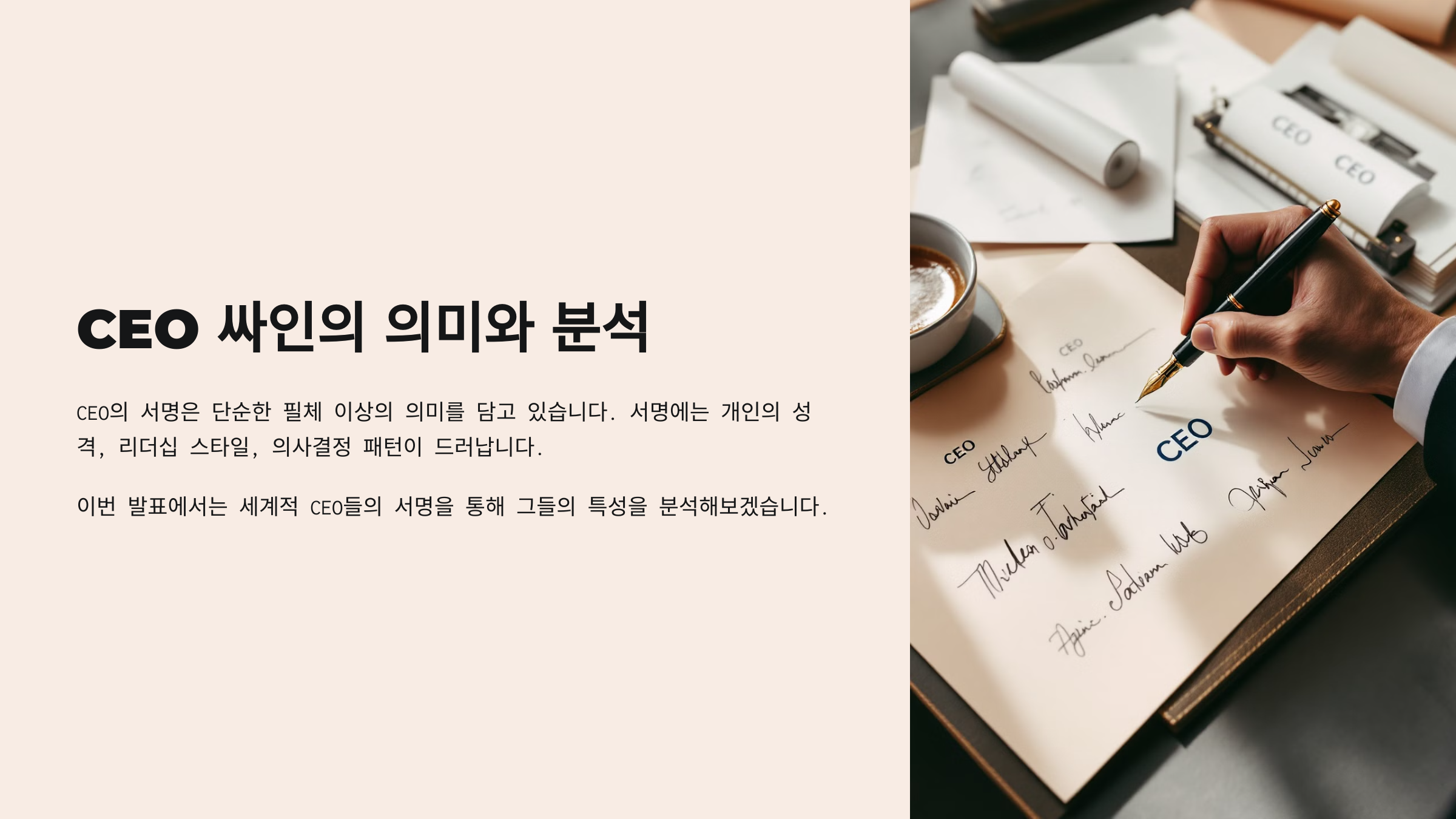
CEO들의 싸인은 단순한 서명이 아니라 그들의 리더십, 브랜드, 비전을 반영하는 요소예요. 싸인의 스타일만 봐도 그 사람의 성격과 경영 철학을 어느 정도 유추할 수 있어요. 🖋️
예를 들어, 빌 게이츠의 싸인은 정갈하고 깔끔한 반면, 일론 머스크의 싸인은 빠르고 역동적이죠. 이처럼 싸인은 단순한 이름의 기록이 아니라 CEO의 아이덴티티를 나타내는 상징이 될 수 있어요. 🔥
📌 CEO들의 싸인이 주는 의미 🔍
싸인 스타일 특징 대표 CEO 깔끔하고 정갈한 싸인 가독성이 뛰어나고 신뢰감을 줌 빌 게이츠 빠르고 다이나믹한 싸인 창의적이고 도전적인 이미지 일론 머스크 심플한 미니멀 스타일 최소한의 획으로 효율성을 강조 스티브 잡스 곡선적이고 부드러운 싸인 유연성과 협업을 중시하는 경영 스타일 제프 베이조스 이제 CEO들의 싸인이 어떤 의미를 가지는지 알았어요! 그럼 먼저, 빌 게이츠의 싸인을 분석해 볼까요? 🔍
빌 게이츠의 싸인 분석 🖋️
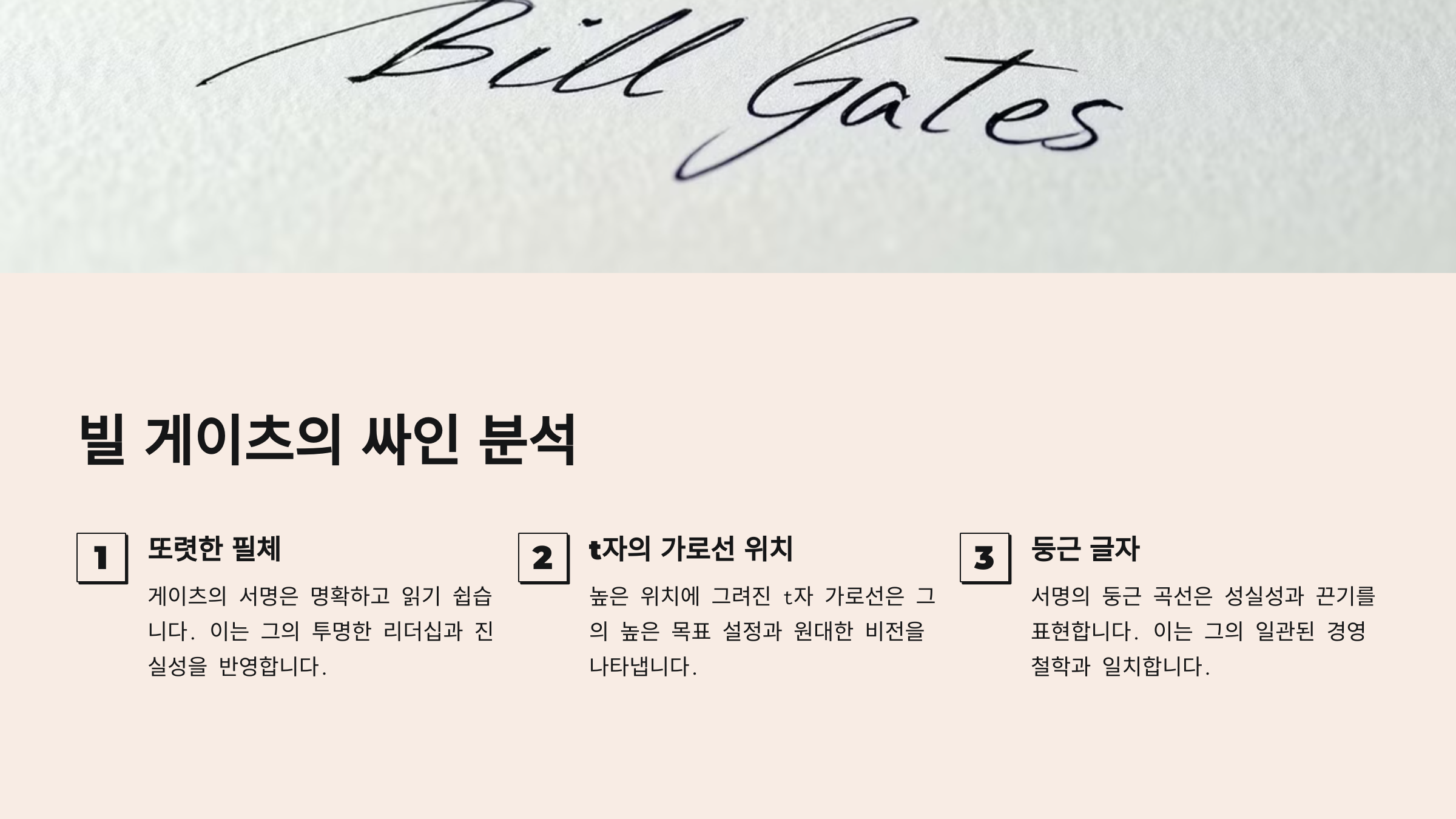
빌 게이츠(Bill Gates)는 마이크로소프트(Microsoft)의 공동 창립자로, 그의 싸인은 그의 성격과 경영 철학을 반영하고 있어요. 💡
그의 싸인은 깔끔하고 정갈한 글씨체로 되어 있으며, 가독성이 뛰어나고 신뢰감을 주는 것이 특징이에요. 이는 그가 논리적이고 체계적인 사고를 중시하는 리더라는 점을 보여줘요. 📜
📌 빌 게이츠 싸인의 주요 특징 ✅
특징 설명 가독성이 뛰어난 필기체 한 글자 한 글자가 명확하게 보이며 정돈됨 깔끔하고 균형 잡힌 구조 획이 정렬되어 있으며 일관성이 유지됨 부드럽지만 강한 마무리 끝부분이 확실하게 닫혀 있어 신뢰감을 줌 논리적인 성향 반영 체계적이고 실용적인 스타일 빌 게이츠의 싸인은 가독성 있는 스타일을 선호하는 사람들에게 좋은 참고 자료가 돼요. 그럼 이제 일론 머스크의 싸인은 어떻게 다를까요? 🚀
일론 머스크의 싸인 분석 🚀
일론 머스크(Elon Musk)는 스페이스X, 테슬라, 뉴럴링크 등의 CEO로, 그의 싸인은 그의 혁신적이고 도전적인 성향을 반영하고 있어요. 💡
그의 싸인은 빠르게 휘갈겨 쓴 듯한 다이나믹한 필체로, 강한 추진력과 변화를 추구하는 그의 성격을 잘 보여줘요. 이는 즉흥적이지만 강한 결단력을 가진 리더의 스타일을 나타내죠. ⚡
📌 일론 머스크 싸인의 주요 특징 ✅
특징 설명 빠르고 역동적인 필기체 획이 길고 속도감이 느껴지는 스타일 약간의 불규칙성 즉흥적인 스타일로 변화와 혁신을 상징 강한 획과 강조된 마무리 마지막 획이 강조되어 강한 리더십을 표현 개성 넘치는 스타일 전형적인 형식을 따르지 않고 자유롭게 구성됨 일론 머스크의 싸인은 창의적이고 독창적인 스타일을 원하는 사람들에게 좋은 참고 자료가 돼요. 그럼 이제 스티브 잡스의 싸인은 어떻게 다를까요? 🍏
스티브 잡스의 싸인 분석 🍏
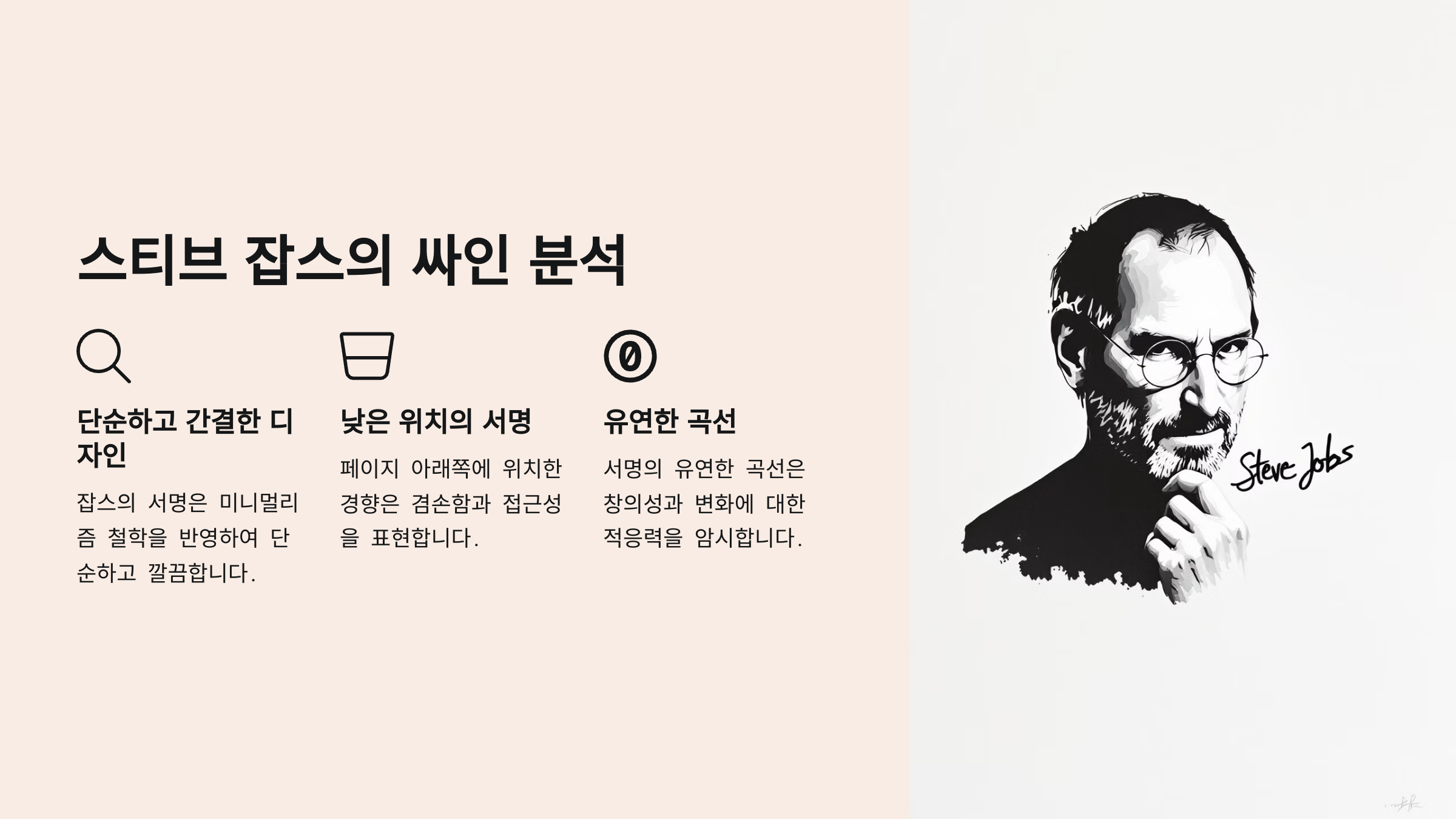
스티브 잡스(Steve Jobs)는 애플(Apple)의 공동 창립자이자 혁신적인 기업가로 유명해요. 그의 싸인은 그의 미니멀한 철학과 심플한 디자인 원칙을 반영하고 있죠. 🎨
잡스의 싸인은 단순하지만 강한 개성을 가진 필기체로 이루어져 있으며, 특히 획이 일정하고 명확한 글씨체가 특징이에요. 이는 그가 불필요한 것을 제거하고 본질만 남기는 사고방식을 가지고 있었다는 걸 보여줘요. ✍️
📌 스티브 잡스 싸인의 주요 특징 ✅
특징 설명 미니멀한 디자인 불필요한 장식 없이 깔끔하고 단순한 서체 일관된 글씨체 획이 고르게 유지되며 정리된 느낌 강한 개성과 명확한 구조 획이 과하지 않으면서도 강한 인상을 줌 균형 잡힌 형태 전체적으로 정돈된 느낌을 줌 스티브 잡스의 싸인은 심플하면서도 개성이 강한 싸인을 원하는 사람들에게 좋은 참고 자료가 돼요. 그럼 이제 제프 베이조스의 싸인은 어떻게 다를까요? 🚀
제프 베이조스의 싸인 분석 🚀
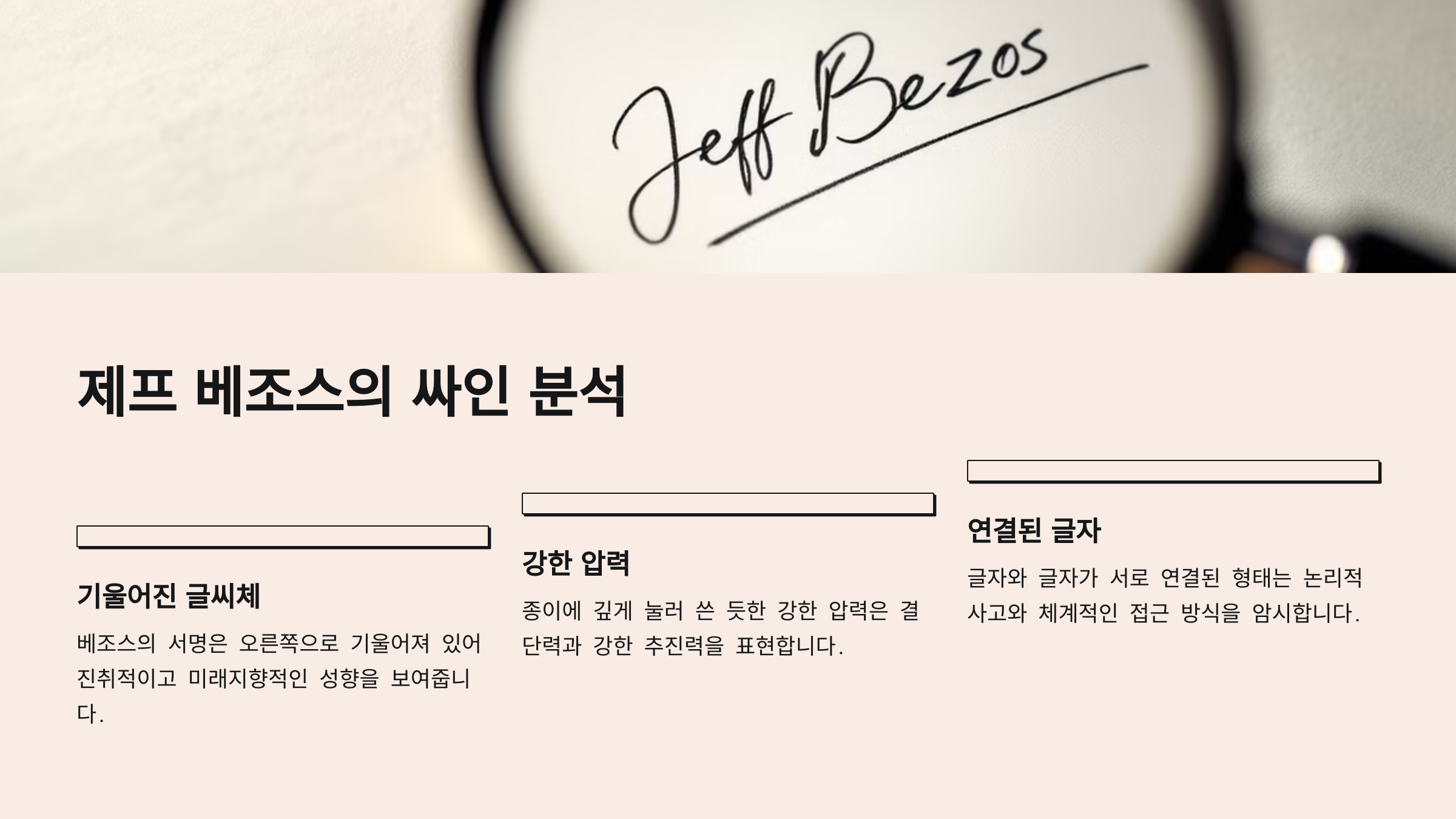
제프 베이조스(Jeff Bezos)는 아마존(Amazon)의 창립자이자 전 CEO로, 그의 싸인은 유연하면서도 힘 있는 필체를 보여줘요. 📦
베이조스의 싸인은 곡선이 많고 부드러운 필기체로 이루어져 있으며, 특히 글자 사이가 넓고 흐름이 자연스럽게 연결되는 것이 특징이에요. 이는 그가 장기적인 비전과 유연한 사고를 가진 리더라는 점을 반영하죠. 💡
📌 제프 베이조스 싸인의 주요 특징 ✅
특징 설명 곡선이 많은 필기체 글자가 부드럽게 연결되며 자연스러운 흐름 유지 넓은 글자 간격 공간을 넉넉하게 사용하여 개방적인 느낌을 줌 유연하면서도 힘 있는 스타일 부드러움 속에서도 강한 결단력을 표현 비전과 혁신의 상징 장기적인 목표를 중요시하는 스타일 제프 베이조스의 싸인은 부드러우면서도 리더십이 강한 스타일을 원하는 사람들에게 좋은 참고 자료가 돼요. 그럼 이제 성공한 CEO들의 싸인 특징을 정리해 볼까요? 📊
성공한 CEO들의 싸인 특징 📊
지금까지 다양한 CEO들의 싸인을 분석하면서, 그들의 성격과 경영 철학이 싸인에 어떻게 반영되는지 살펴봤어요. ✍️
이제 성공한 CEO들의 싸인의 공통적인 특징을 정리해볼게요. 이 원칙을 참고하면, 자신만의 강렬한 싸인을 디자인하는 데 도움이 될 거예요! 🚀
📌 CEO 싸인의 공통된 특징 ✅
특징 설명 대표 CEO 가독성이 뛰어난 스타일 명확하고 정돈된 서체를 사용하여 신뢰감을 줌 빌 게이츠 빠르고 역동적인 필기체 획이 강하고 속도감이 느껴지는 스타일 일론 머스크 미니멀하고 단순한 디자인 불필요한 요소를 제거하고 본질을 강조 스티브 잡스 유연하면서도 강한 필체 곡선이 많고 흐름이 자연스러운 스타일 제프 베이조스 CEO들의 싸인을 참고하면, 신뢰감 있는 비즈니스 스타일부터 혁신적이고 창의적인 스타일까지 다양한 방향으로 싸인을 만들 수 있어요! 💡
마지막으로, 싸인과 관련된 자주 묻는 질문(FAQ)을 정리해볼게요. 📢
FAQ
Q1. CEO들의 싸인은 왜 중요한가요?
A1. 싸인은 단순한 서명을 넘어 리더십과 브랜드 가치를 반영하는 요소예요. CEO들의 싸인은 신뢰감, 추진력, 혁신성을 나타낼 수 있어요. 💼
Q2. 싸인을 만들 때 CEO들의 스타일을 참고하면 도움이 될까요?
A2. 네! 가독성이 좋은 싸인, 역동적인 싸인, 미니멀한 싸인 등 원하는 스타일을 선택하는 데 유용해요. 🔍
Q3. 싸인을 바꿔도 괜찮을까요?
A3. 네, 하지만 공식 문서나 계약서에 사용하는 싸인은 일관성을 유지하는 것이 좋아요! 📜
Q4. CEO들의 싸인에서 가장 중요한 요소는 무엇인가요?
A4. 명확성, 개성, 속도감, 신뢰감이 가장 중요한 요소예요. CEO들은 자신들의 철학을 싸인에 반영하죠. ✍️
Q5. 빠르고 강한 필체가 주는 의미는?
A5. 결단력이 강하고 추진력이 있는 성격을 나타내요. 일론 머스크처럼 역동적인 스타일을 원한다면 필체를 빠르게 연습해 보세요! ⚡
Q6. 가독성이 좋은 싸인은 어떤 사람에게 적합한가요?
A6. 비즈니스 환경에서 신뢰를 주고 싶은 사람들에게 좋아요. 빌 게이츠처럼 정돈된 스타일을 참고하면 도움이 돼요. 🏢
Q7. 싸인을 연습할 때 가장 중요한 점은?
A7. 일관성을 유지하면서 자연스럽게 연습하는 것이 중요해요. 반복적으로 연습하면 자신만의 싸인이 손에 익어요. 🖋️
Q8. 싸인에 추가적인 요소(밑줄, 별 등)를 넣어도 될까요?
A8. 네! 하지만 너무 많은 장식은 가독성을 해칠 수 있으니 적절한 크기와 디자인을 유지하는 것이 좋아요. ⭐